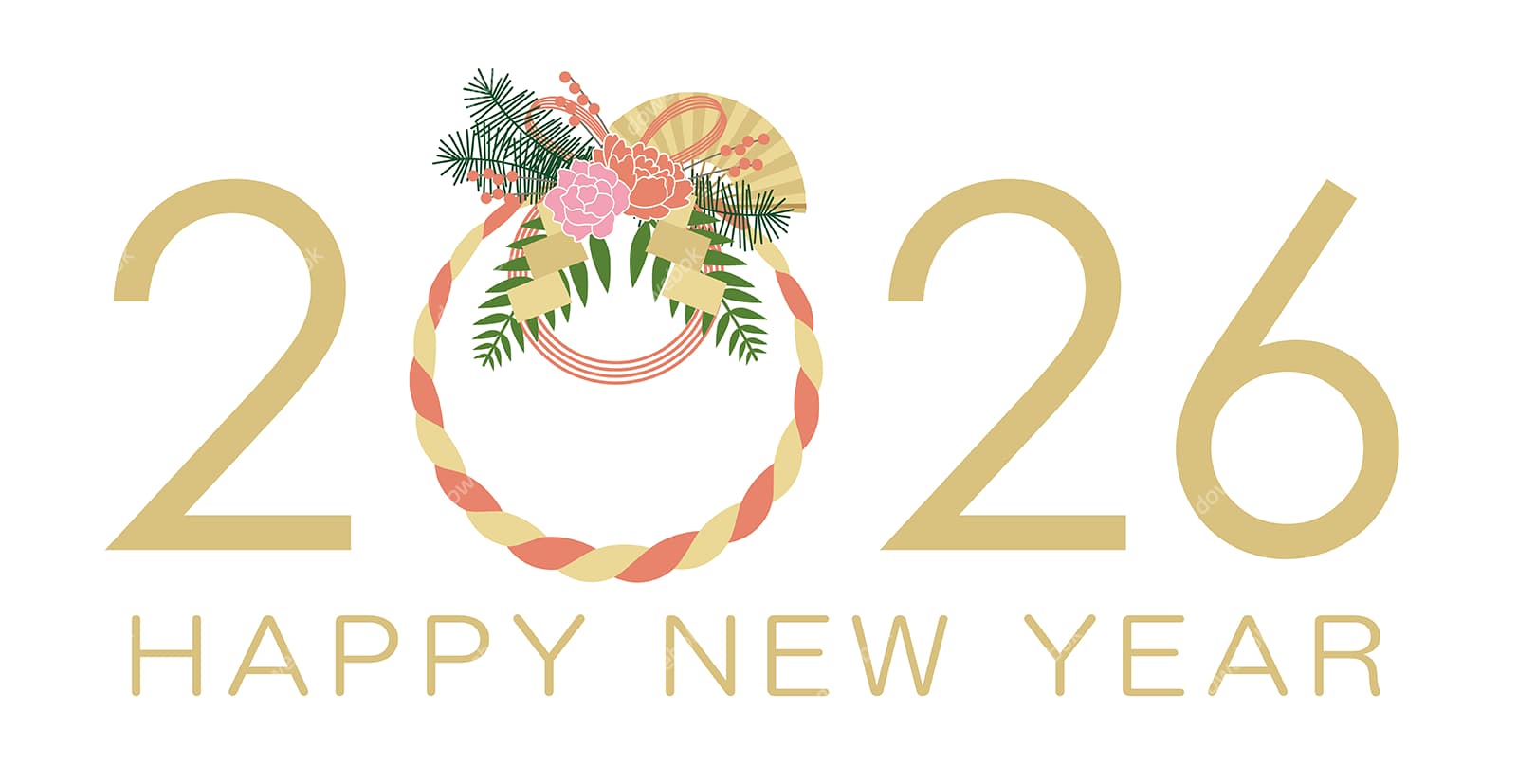
这是一款简约花卉和数字设计 2026 新年快乐素材,纯白背景上,浅金 “2026” 字体简约柔和,数字 “0” 化作日式注连绳装饰,搭配松枝、花卉,透出和风新年的雅致氛围。下方衬着同色系的 “Happy New Year”,整体以淡金配色 + 传统装饰元素,既显跨年的清新温馨,又用和风细节透出独特的节日质感,简约且有格调。